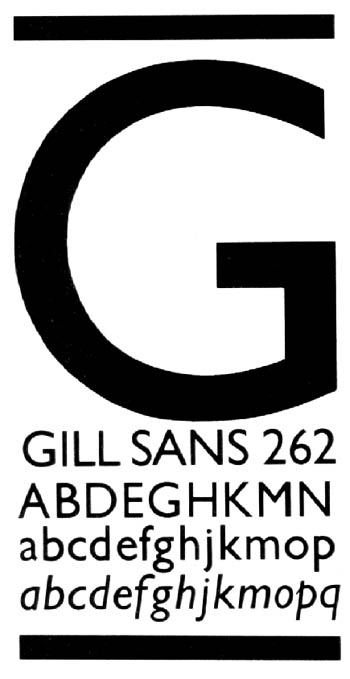
Gill Sans (Eric Gill, 1928)
Apresentada ao comércio em 1928 e logo apupada como representante de «typographical bolchevism», a Gill Sans acabou por ser a única grotesca que se conseguir afirmar na Inglaterra contra a forte competição que lhe vinha da Alemanha por exemplo em forma da Akzidenz Grotesk, que era a letra favorita dos bauhausianos. Este facto é ainda mais notável se considerarmos que Eric Gill não era nenhum vanguardista em termos estéticos, mais era um tipógrafo conservador, que desenhou várias romanas serifadas de inspiração renascentista. A Gill Sans foi a única fonte sem serifa que Eric Gill desenhou e portanto pode ser considerada mesmo uma excepção na sua obra tipográfica.
A Gill Sans nasceu sob a influência do mestre Edward Johnston, que tinha desenhado a muito parecida London Transport. Gill admitiu a forte influência de Johnston, mas argumentou que a sua letra representava um melhoramento na lógica dos meios de produção modernos. Depois de alguns protótipos desenhados para a tabuleta da loja de um amigo de Gill, a primeira aplicação da Gill Sans aperfeiçoada foi na London & North Eastern Railway. Encomendada pela LNER, a Gill Sans foi usada para toda a sinalética, displays, horários e publicidade. Em todos estes ambientes «funciona» bem, afirmando-se como uma fonte genuinamente universalista. Uma fonte que combina a destreza do gravador de letras lapidares com a fineza do desenho de letras caligráficas. A brutal Gill Extra Bold, que o próprio Gill autocriticamente chamou Double Elephants, foi comentada no seu Essay on Typography: «There are now as many different varieties of letters as there are different kinds of fools. I myself am responsible for designing five different sorts of sans-serif letters each one thicker and fatter than the last because every advertisement has to try to shout down its neighbours». (A retórica de Gill é tão famosa como as suas letras). |
O uso da Gill Sans generalizou-se para todas as aplicações; como tem sido objecto de intenso revivalismo, não só a vemos em displays, anúncios e títulos, como também a encontramos com alguma frequência em textos corridos. Hoje, a Gill Sans «is still going strong», sendo especialmente bem apreciada no Reino Unido, usada pela BBC, por inúmeras outras instituições e por muitas empresas comerciais.
Num recente posting, Ben Archer discutiu o que seriam as «Gill Sans Alternatives»E sugeiru as seguintes altenativas: Gill Sans by Eric Gill for Monotype (1932) The OpenType Pro version released in 2005 offers multilingual and cross-platform support, but no additional Western glyphs besides an alternate numeral 1. Granby by Stephenson Blake (metal in 1930) Stephenson Blakes competitor to Gill Sans is actually closer to Johnston. As Archer informs, this is probably because they cut the wooden masters for the original Underground lettering. Granby is probably the most underused of the alternatives on this list. Highly recommended. [MyFonts] [Veer] Bliss by Jeremy Tankard (1996) Probably the most complete and usable of these alternatives, Bliss improves on nearly every failing in Johnston and Gill Sans. Its also a great replacement for Frutiger and Syntax. Forms were chosen for their simplicity, legibility, and Englishness. See also Tankards Wayfarer, inspired by Granby. Foundry Sterling by David Quay and Freda Sack for The Foundry Released a few years after Bliss, Sterling seemed like a bit of a bandwagon jumper, but it has its own merits. Agenda by Greg Thompson for Font Bureau (19932000) The first Gill Sans follower with digital origins, Agenda is highly regularized for text settings with expanded weights and widths, but maintains some Johnston idiosyncrasy like the diamond dots. P22 London Underground by Rich Kegler for P22 (1997) A direct digitization of the original Johnston letters. ITC Johnston by David Farey for ITC (19992002) Fareys font family does the best job of all the interpretations in adapting Johnstons alphabet for modern use. [MyFonts] [FontShop] English Grotesque (1998) by Rian Hughes for Device. An exaggerated interpretation by the British comic book artist and letterer. [MyFonts] [Veer] [FontShop] Tschichold by Jan Tschichold, Thierry Puyfoulhoux (1933, 2001) Its not widely known that Jan Tschichold, famous for Sabon, first drew a face heavily inspired by Gill Sans. An interesting and underused revival by Puyfoulhoux |